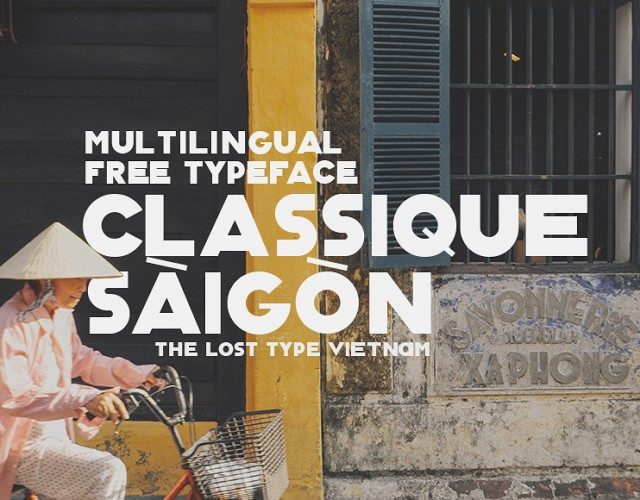
Giới thiệu về Font việt hoá Classique Saigon Typeface
Trong thế giới thiết kế đồ họa, việc tìm kiếm một Font Chữ mang đậm hơi thở văn hóa Việt Nam luôn là ưu tiên hàng đầu. Font việt hoá Classique Saigon Typeface là một tác phẩm nghệ thuật tiêu biểu, được lấy cảm hứng từ những tấm biển quảng cáo vẽ tay tại Sài Gòn những năm 1950-1960. Với những đường nét hình học cứng cáp nhưng vẫn giữ được sự uyển chuyển đặc trưng, bộ phông này giúp tái hiện không gian xưa cũ đầy hoài niệm cho các dự án sáng tạo hiện đại.
Đặc điểm nổi bật của bộ font
Được thực hiện bởi nhà thiết kế Mạnh Nguyễn, Classique Saigon không chỉ đơn thuần là bộ chữ cái mà còn là sự kết tinh của lịch sử. Các ký tự được điều chỉnh tỉ mỉ để phù hợp hoàn toàn với bảng mã tiếng Việt, đảm bảo không lỗi dấu khi sử dụng trên các phần mềm như Adobe Photoshop hay Illustrator. Phong cách Retro và Vintage mà bộ font này mang lại cực kỳ phù hợp cho các thiết kế poster phim, bìa sách hoặc bảng hiệu quán cà phê.
Ứng dụng Font việt hoá Classique Saigon Typeface trong thiết kế
Việc sử dụng Font việt hoá Classique Saigon Typeface mang đến sự độc đáo và cá tính riêng biệt cho sản phẩm. Đối với các bạn học sinh và sinh viên, đây là công cụ đắc lực để trang trí bài thuyết trình hoặc làm báo tường thêm phần sinh động. Những đường nét đậm, rõ ràng giúp thông điệp truyền tải trở nên mạnh mẽ và dễ đọc hơn bao giờ hết.
Để tận dụng tối đa vẻ đẹp của Classique Saigon, bạn nên kết hợp với các tông màu trầm như vàng nghệ, đỏ gạch hoặc xanh rêu. Sau khi tải tệp tin về máy tính, bạn chỉ cần giải nén và cài đặt trực tiếp vào hệ thống để bắt đầu sáng tạo. Đây thực sự là lựa chọn hoàn hảo cho những ai yêu mến vẻ đẹp cổ điển của hòn ngọc Viễn Đông.